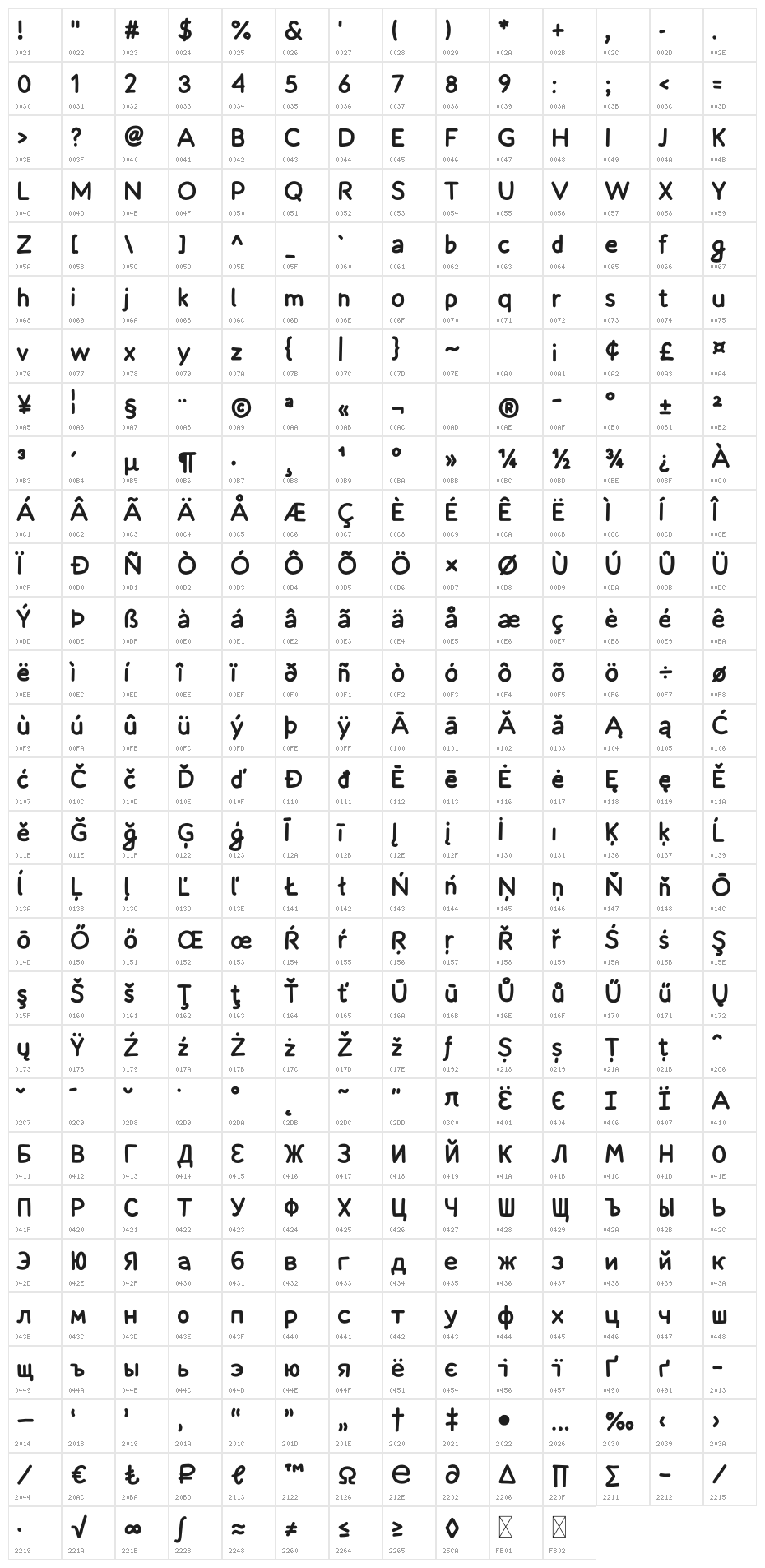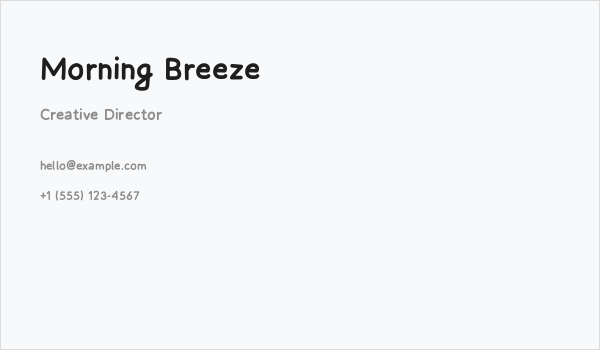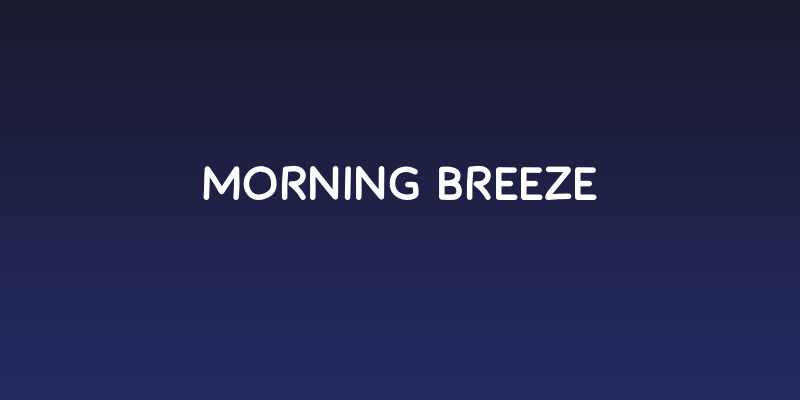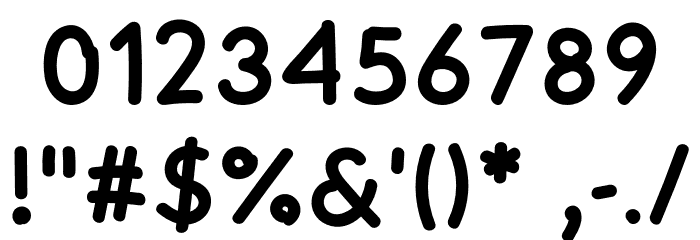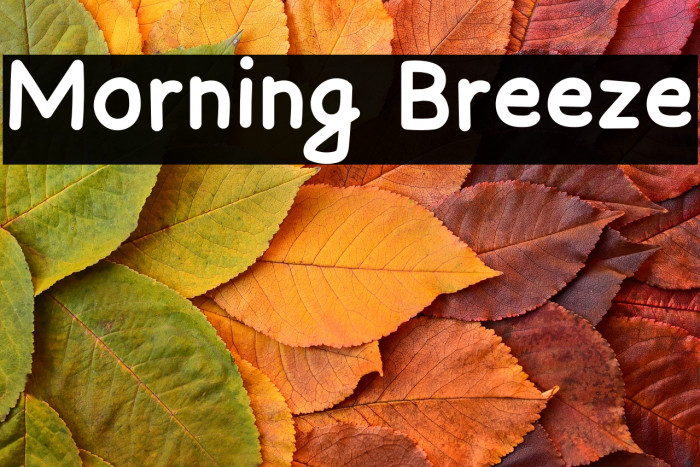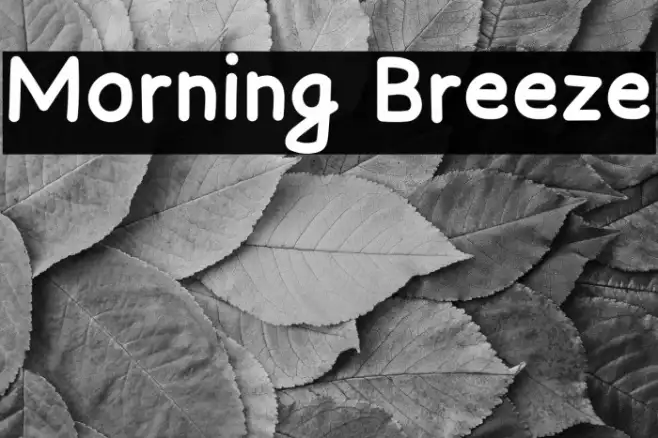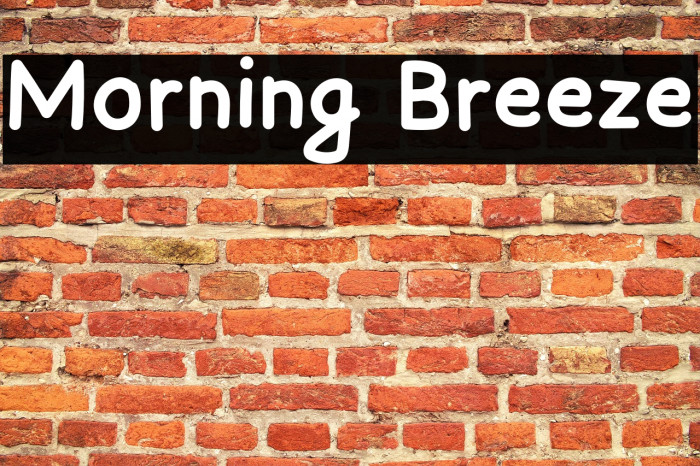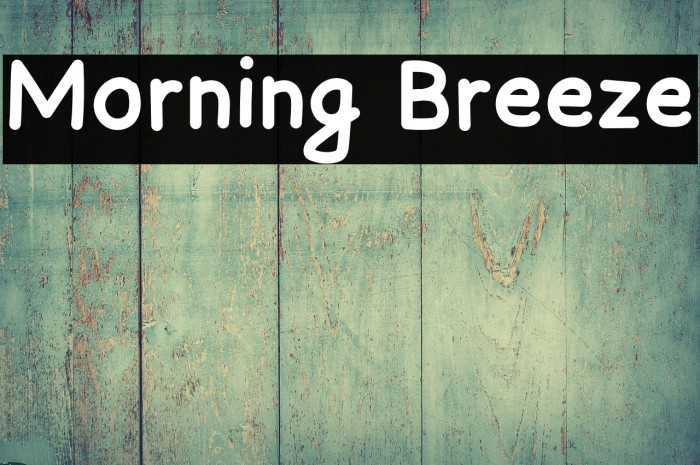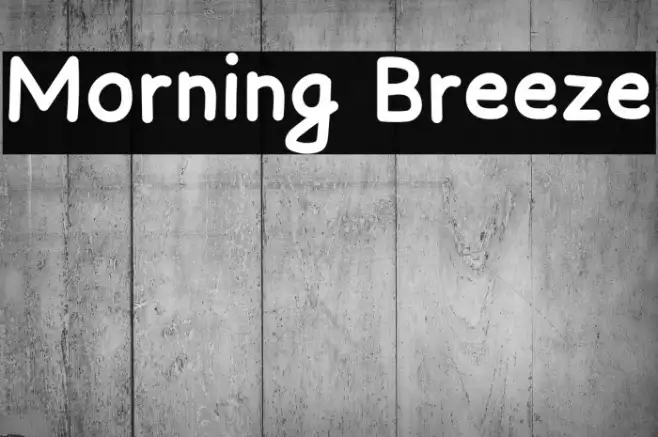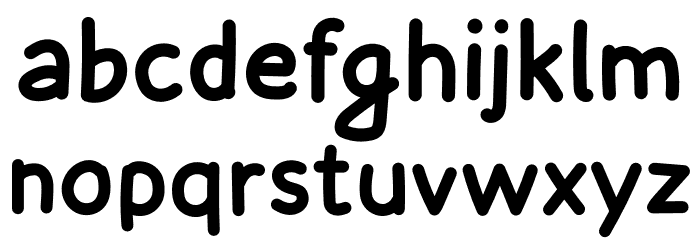
Morning Breeze Font
| Estilo general | Playful |
| Caso de uso | Headlines, Logos, Casual Text |
| Proyectos propuestos | Ideal for children's books, playful branding, casual invitations, and social media graphics. |